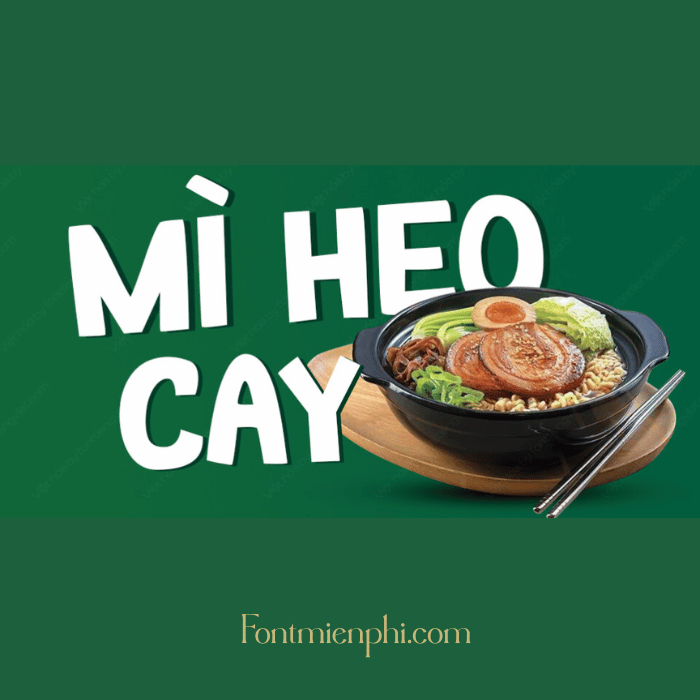
Font Việt hóa 1FTV VIP Bingo – Phong Cách Độc Đáo, Thiết Kế Chuyên Nghiệp
Font Việt hóa 1FTV VIP Bingo là bộ font chữ đẹp, độc đáo, hỗ trợ đầy đủ tiếng Việt, phù hợp cho thiết kế đồ họa, in ấn, banner, logo và nhiều dự án sáng tạo khác. Với kiểu chữ ấn tượng, nét thanh – đậm cân đối, 1FTV VIP Bingo giúp sản phẩm của bạn trở nên nổi bật và chuyên nghiệp hơn.
✔ Nhiều phong cách đa dạng – Phù hợp với nhiều mục đích sử dụng.
✔ Chất lượng sắc nét – Hiển thị đẹp trên mọi chất liệu in ấn.